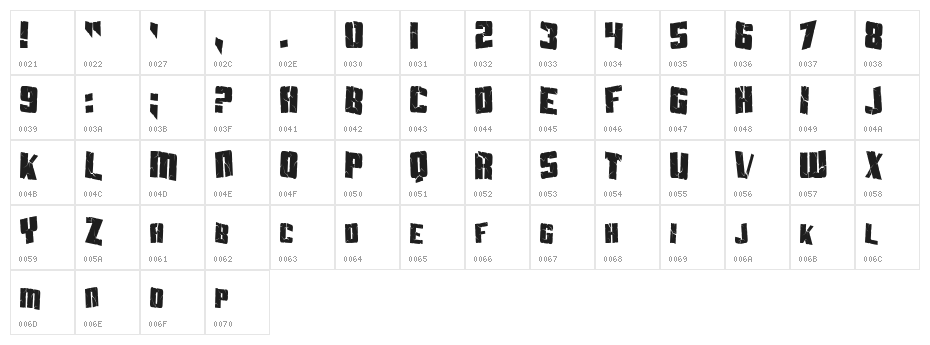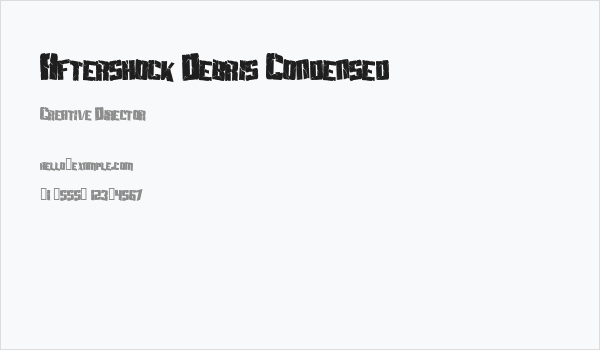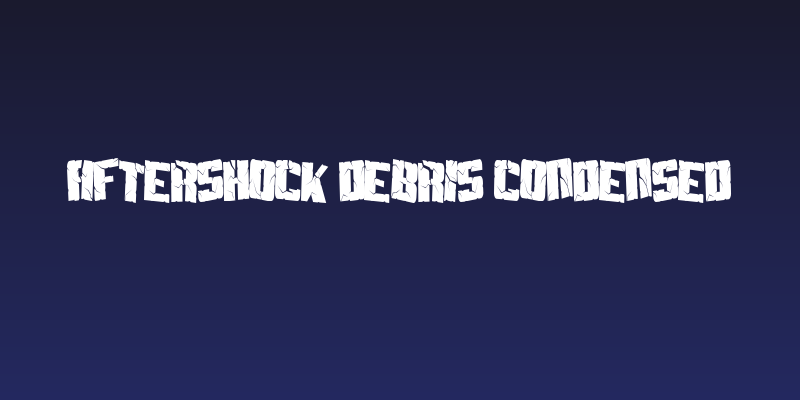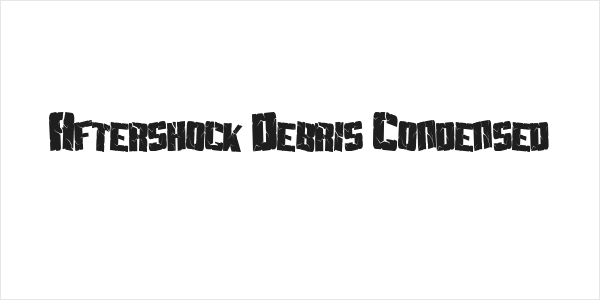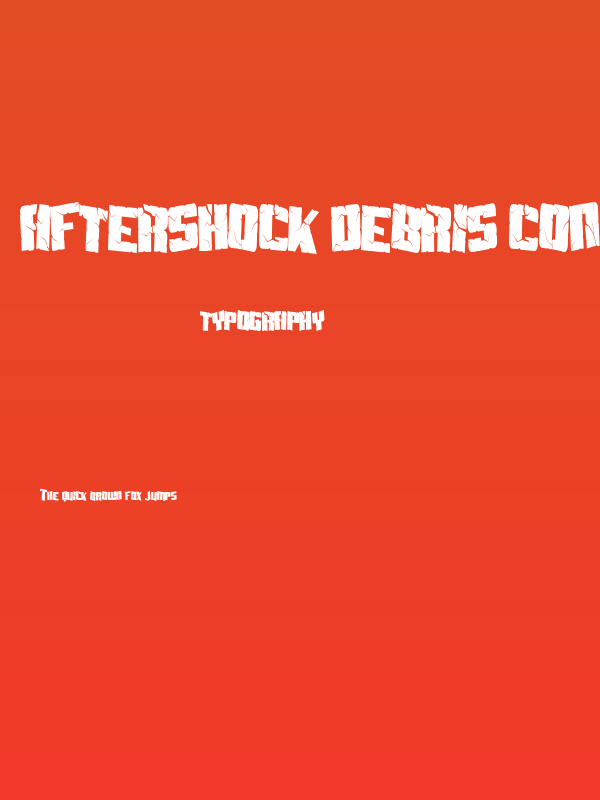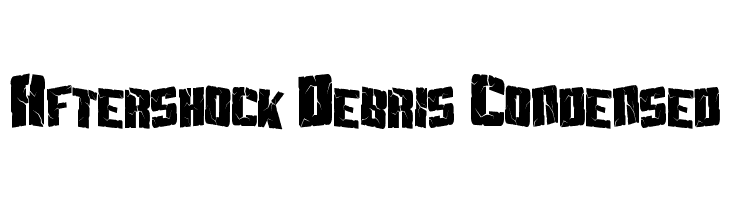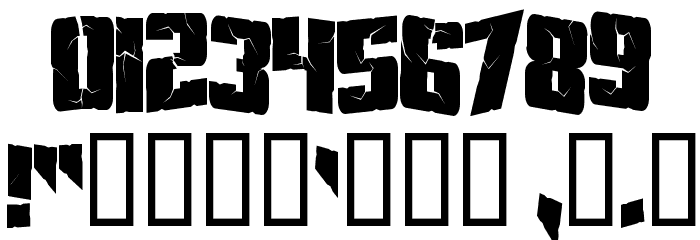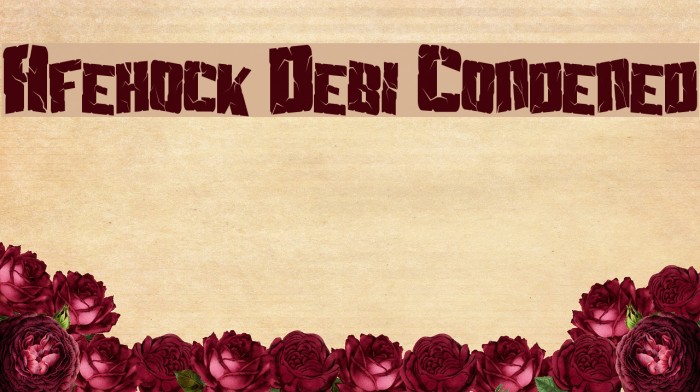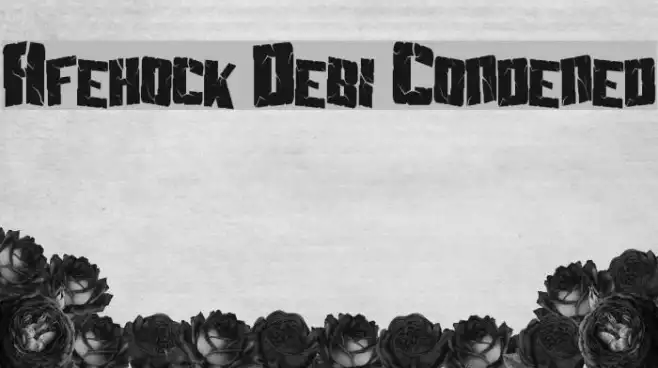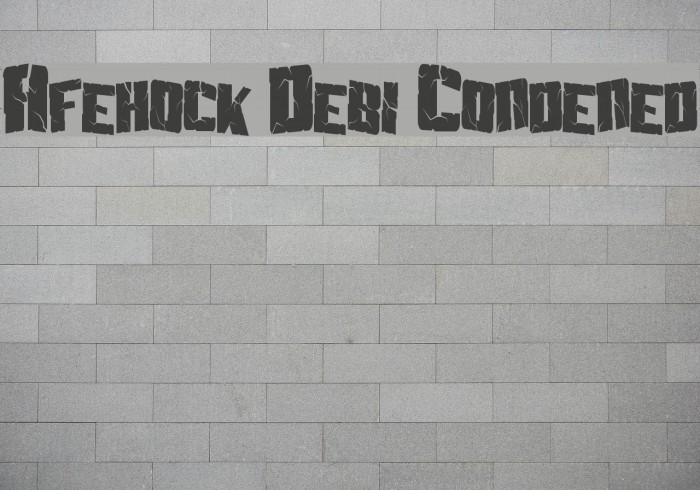
Aftershock Debris Condensed Font
| Projets proposés | Ideal for use in posters, album covers, video game graphics, and any project needing a dramatic, edgy look. |